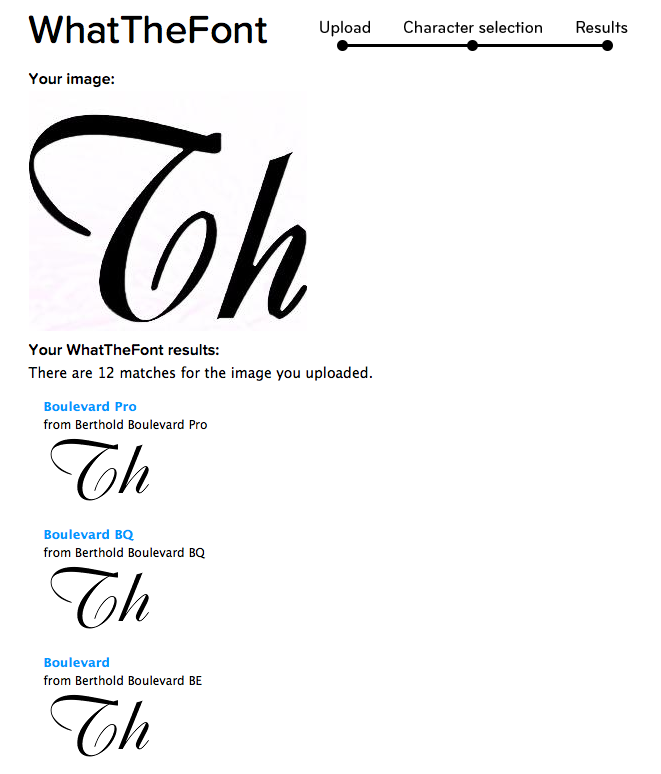
Wer kann mir sagen, welche Schrift das ist
Vielen Dank erst einmal. Die Schrift passt noch nicht ganz genau..... habe noch mal den ganzen Schriftzug hochgeladen.
Oder gibt es einen Trick???
Wie Carmen schon sagt: da wurde auch noch kräftig dranrum operiert. In Illustrator oder einem ähnlichem Programm solltest du durch Stauchung/Kontur und leichte Korrekturen den Schriftzug problemlos nachbauen können.
(Ob das dann zu empfehlen ist, steht auf einem anderen Blatt. Die Details dieses Schriftzuges sind ziemlich gruselig.)
Die Details dieses Schriftzuges sind ziemlich gruselig.)
Und das ist dann noch sehr gelinde gesagt. Sieht aus wie einer Laubsägenarbeit aufgrund einer schlecht aufgelösten Bilddatei. So in der Art von: „Der Entwurf ist OK, muss aber noch mal eben gephotoshopped werden“ > Auf dem nächsten Schreibtisch heißt es dann: „Wieviel Pixel? Das können wir so groß nicht ausdrucken, das muss hier erst mal einer vektorisieren …“